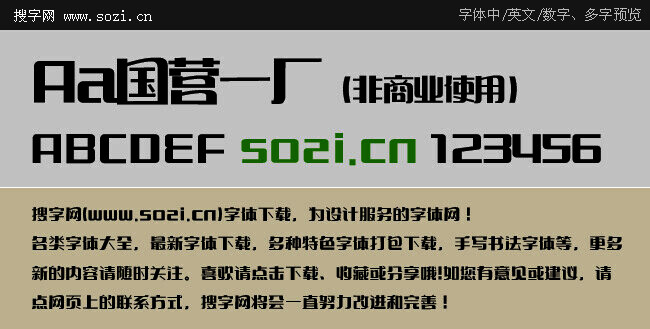
Aa國(guó)營(yíng)一廠(chǎng)
搜字網(wǎng)給大家提供一款A(yù)a國(guó)營(yíng)一廠(chǎng)(非商業(yè)使用)中文字體下載,該字體是一款中文藝術(shù)字體,字體以粗細(xì)筆畫(huà)的秩序性規(guī)劃為基礎(chǔ),巧妙地融合了工業(yè)理性氣質(zhì)與藝術(shù)美感。其字形剛勁有力,線(xiàn)條簡(jiǎn)潔利落,彰顯著一種刻板卻不呆板的工業(yè)風(fēng)格。適合圖書(shū)設(shè)計(jì)、卡通包裝、海報(bào)設(shè)計(jì)等應(yīng)用(此字體為個(gè)人非商用版,商用可以聯(lián)系QQ:1006760504)。